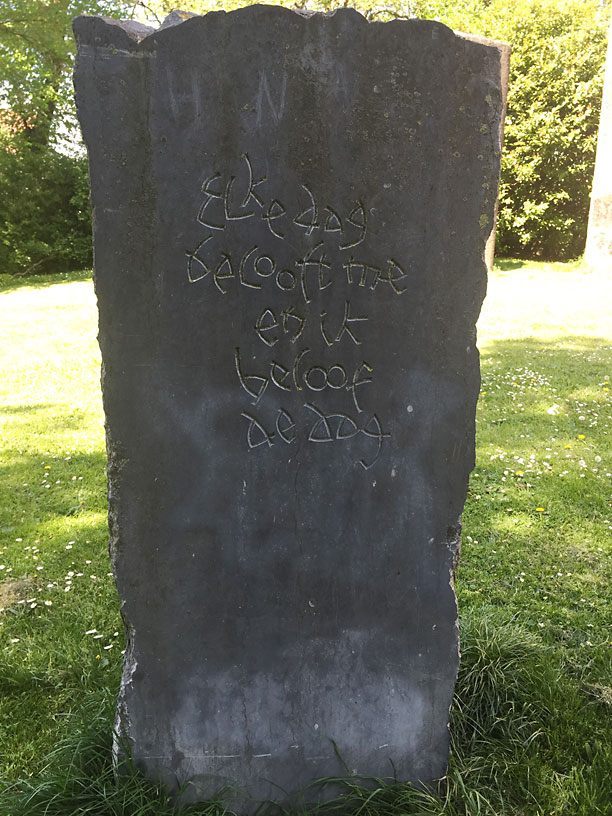
En un paseo que realicé en Mayo de 2016 con un amigo por la ciudad belga de Brujas, encontré por los caminos que rodean la ciudad una frase labrada sobre una piedra (Elke dag belooft me en ik beloof de dag) la fuente me resultó curiosa, interesante y atractiva a la vez para digitalizarla, con un estilo que se podría calificar como rúnico moderno y desenfadado Promenades font es el resultado de este rescate tipográfico.
A partir del dibujado de todas las letras de la frase original y después el resto del alfabeto, números y signos de puntuación, mi objetivo fue conseguir reproducir el estilo de la frase lo más fielmente posible en 4 programas de uso común en diseño gráfico y editorial: InDesign, QuarkXpress, Photoshop e Illustrator).
La cuestión ha resultado más peliaguda de lo que pensé en un principio, pues la frase original contiene 5 letras ‘e’ diferentes, también 3 letras ‘o’, 2 letras ‘k’ y ‘f’, 2 ‘g’ minúsculas, 2 letras ‘b’, 2 ‘l’ minúsculas y además 2 ligaduras: ‘ft’ y ‘oo’ y las quería todas trabajando en la tipografía!! Tuve que echar mano de las funciones OpenType, y no todas compatibles entre los 4 programas de diseño.
Aprovechando la riqueza inicial de caracteres de la frase, me remangué, y fui anotando en una hoja de excel todas las posibles combinaciones contextuales de todo el alfabeto, el que fui probando y eligiendo las mejores ligaduras entre caracteres normales y alternativos, no podía incurrir en cambios redundantes, principalmente con las 5 letras ‘e’ minúsculas y otras tantas otras duplicadas, en un principio con las funciones OpenType: Contextual alternates (calt), Discretionary ligatures (dlig) y Swashes (swsh) lo tenía casi resuelto, pero probando en los diferentes programas de diseño tuve que suplir las carencias de compatibilidad de cada uno y dar solución a más combinaciones alternativas contextuales que la fuente me pedía y a mi me apetecía hacer.
La solución vino con los conjuntos estilísticos (ss00) de los que he creado 3 diferentes, de los swashes contextuales (cswh) para combinar las letras alternativas entre si y la función Stylistic alternates (salt) para suplir la incompatibilidad de Photoshop e Illustrator con los conjuntos estilísticos, soportados por Indesign y desde la versión 2016 por QuarkXpress. El resultado de todo este trabajo es una fuente con multitud de variantes de estilo para crear textos más cercanos a la escritura manual.
Estilo: Script, Caligráfica, manuscrita, jovial
Proporción: Regular
Glyphs: 492
Versión: 1.492
Año de publicación: 2016.
Funciones OpenType: Additional languages, All Alternates, Contextual Swash, Discretionary Ligatures, Historical Forms, Historical Ligatures, Kerning, Localized Forms, Oldstyle Figures, Slashed Zero, Standard Ligatures, Stylistic Alternates, Stylistic Set, Swash, Titling alternates.
La fuente «Promenades» dispone en su versión comercial de un juego de 492 glifos (Latin Extended-A), con soporte para cualquier idioma europeo o centro europeo. Promenades font incluye funciones OpenType para Ligaduras estándar y discreccionales, Números estilo antiguo, 3 Conjuntos estilísticos, Letras alternativas contextuales y Swashes contextuales, etc.
La fuente está dibujada a mano con pincel plano y después digitalizada para su uso en computadoras, es ideal para diseñar posters, titulares llamativos o pequeños textos donde se busque un contraste entre este estilo manual frente a las fuentes neutrales como las sans o las serif.